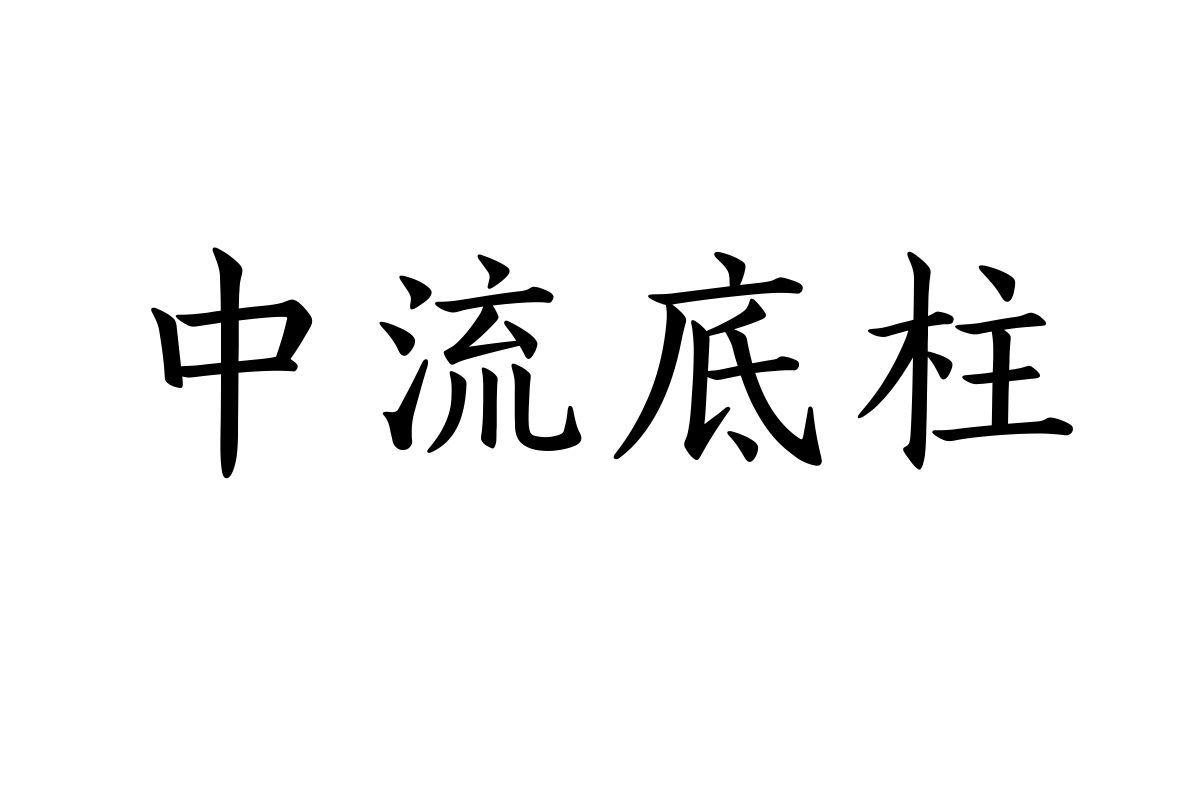
汉仪全唐诗简是一款专为中文诗词创作设计的字体。它采用了经典的楷书风格,线条流畅、结构严谨。这款字体的特点在于其笔画粗细适中,既有楷书的规整感,又不失行书的灵动性,使得书写起来既庄重又不失美感。
在设计上,汉仪全唐诗简注重细节的处理,每个字的间距、笔画的粗细都经过精心设计,使得整个字体看起来既美观又易于阅读。同时,这款字体还保留了一些古风元素,如使用了一些传统的装饰性笔画,使得整体风格更加古朴典雅。
总的来说,汉仪全唐诗简是一款非常适合用于诗词创作和书法创作的字体,无论是用于打印还是电子屏幕显示,都能展现出其独特的魅力。